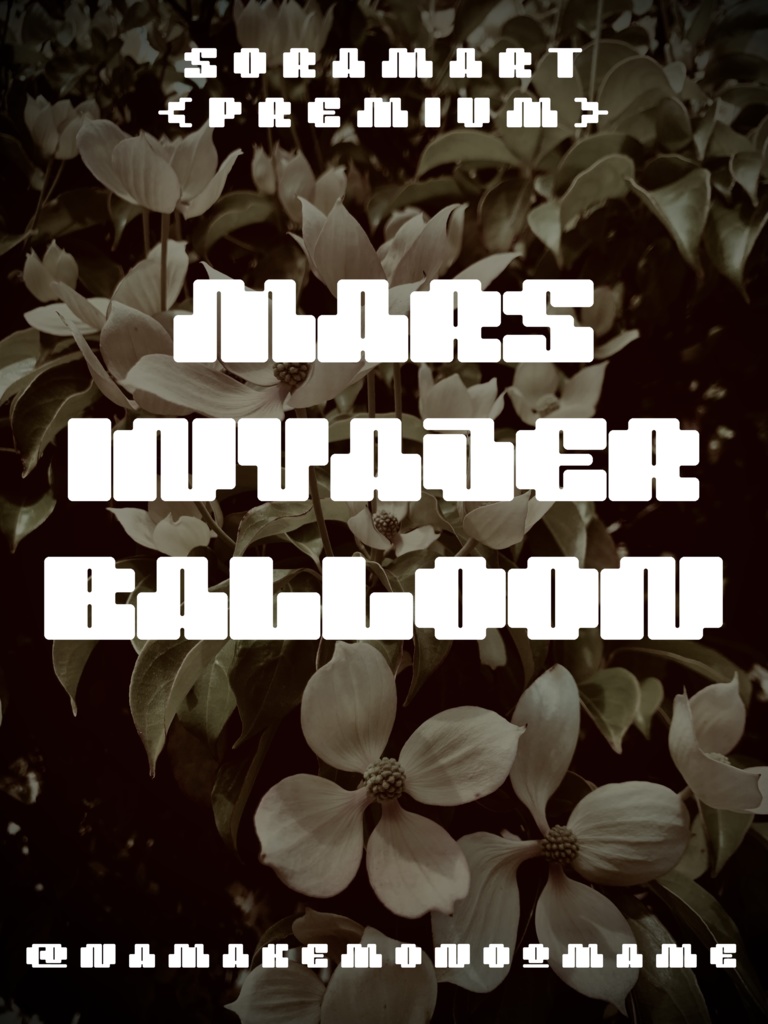
そらマートフォントデータ”Mars Invader Balloon”Digital2,500 JPY카트에 담기기프트 보내기About Giftレトロフューチャーなゲーミング・ポップフォントを、風船のように膨らませたアレンジ版"Mars Invader Balloon" です。 「TrueTypeフォントファイル」という形式です。 ダウンロードした後、Zipファイル内のデータをインストールしてお使いください。 このフォントは商用利用可となっております。 お客様の制作・創作活動のお役に立てれば幸いです。 ※使用上の注意事項などは、添付のReadmeをお読みください。 ※このフォントは、有料販売専用商品です。そらマートVisit FANBOX!Fontsフォントデータ”Crushed Can Serif Empty”そらマート200 JPYFontsフォントデータ”Crushed Can Serif Wide”そらマート0 JPYFontsフォントデータ”Crushed Can Serif”そらマート0 JPYFontsフォントデータ”Dolce Cube Tall”そらマート0 JPYFontsフォントデータ”Dolce Cube”そらマート0 JPYFontsフォントデータ”Eight-bit Quest Wide”そらマート2,500 JPYFontsフォントデータ”Eight-bit Quest”そらマート2,500 JPYFontsフォントデータ”Tonik Crate”そらマート2,500 JPYFontsフォントデータ”Vapor Sprout Edge”そらマート2,500 JPYFontsフォントデータ”Vapor Sprout Wide”そらマート2,500 JPYFontsフォントデータ”Vapor Sprout”そらマート2,500 JPYFontsフォントデータ”Star Shoot Ray”そらマート2,500 JPYFontsフォントデータ”Star Shoot Black Wide”そらマート2,500 JPYFontsフォントデータ”Star Shoot Black”そらマート2,500 JPYFontsフォントデータ”Mars Invader Wide”そらマート2,500 JPYFontsフォントデータ”Mars Invader”そらマート2,500 JPYFontsフォントデータ”Rock Cut Serif”そらマート2,500 JPYFontsフォントデータ”Rock Cut Drop Wide”そらマート2,500 JPYFontsフォントデータ”Rock Cut Drop”そらマート2,500 JPYFontsフォントデータ”Longtail Sans Serif Slashed”そらマート2,500 JPY더보기